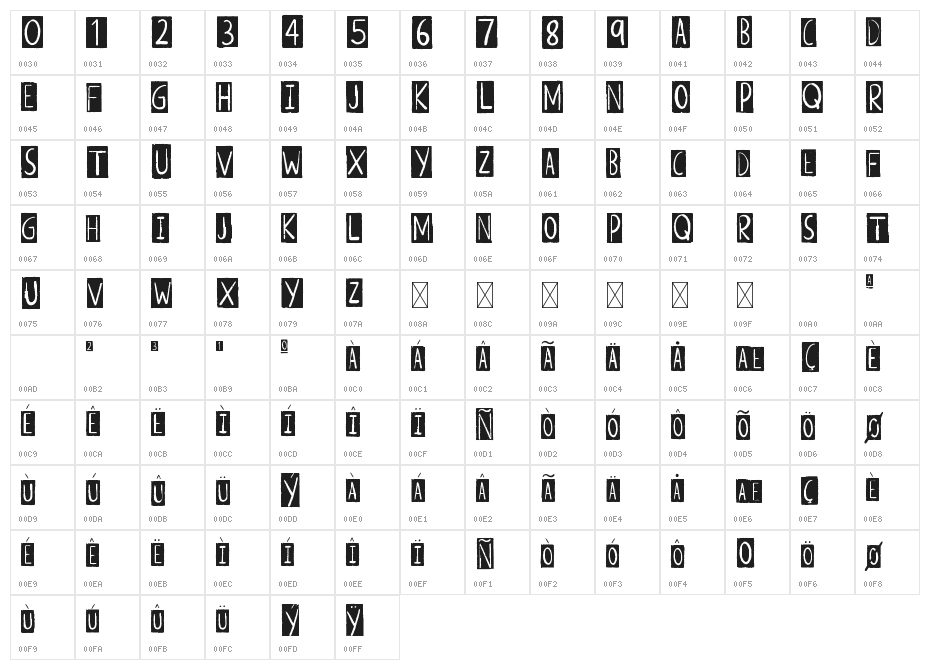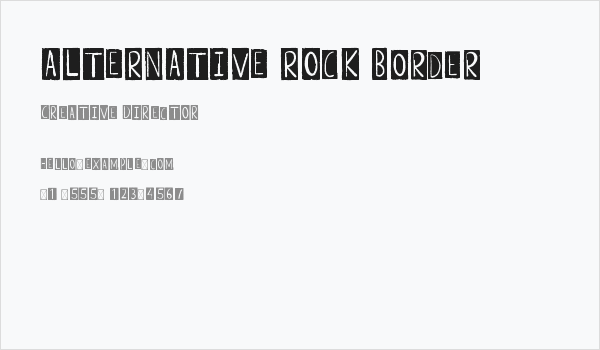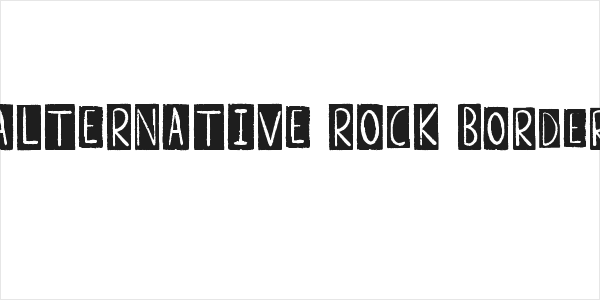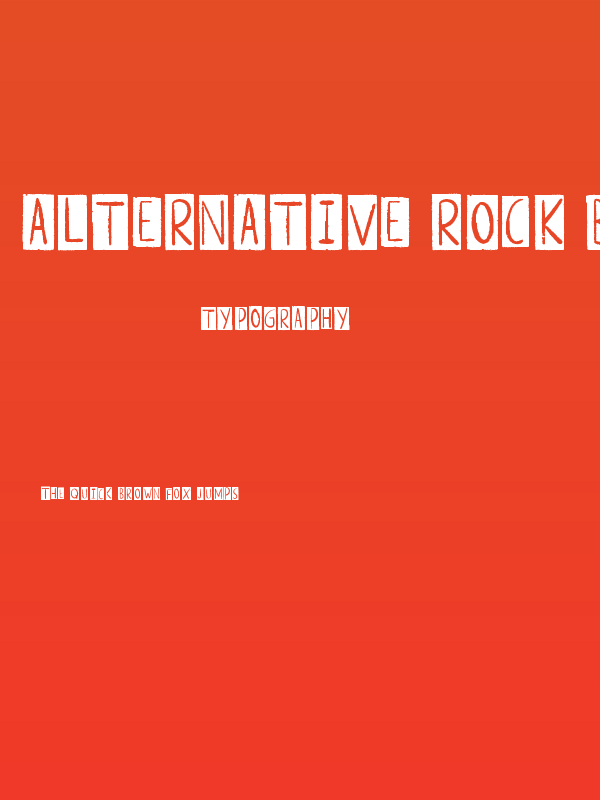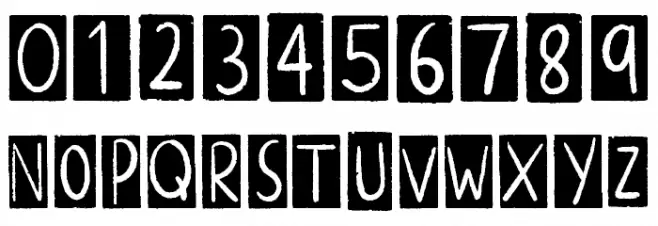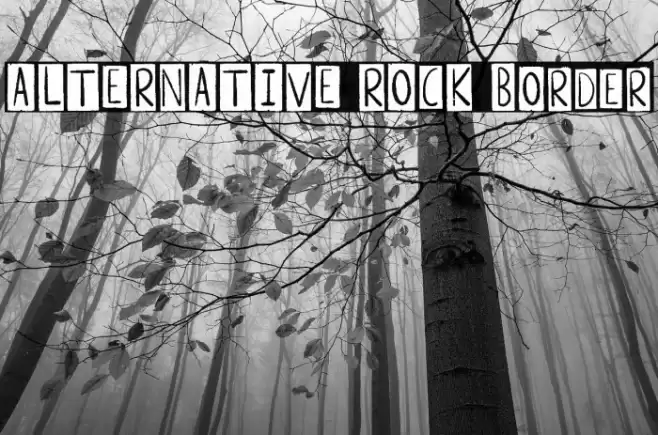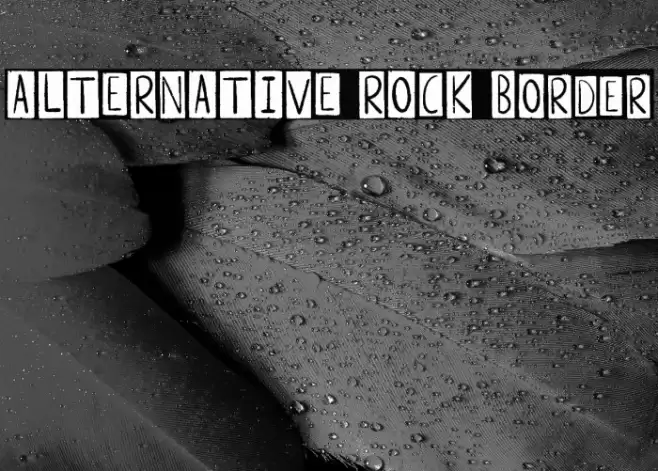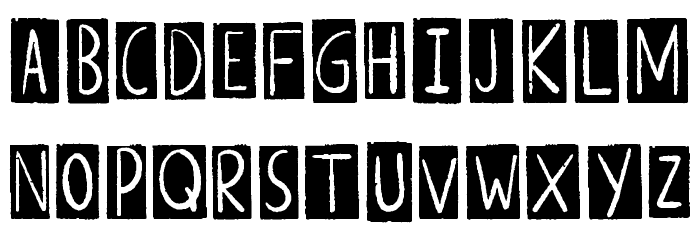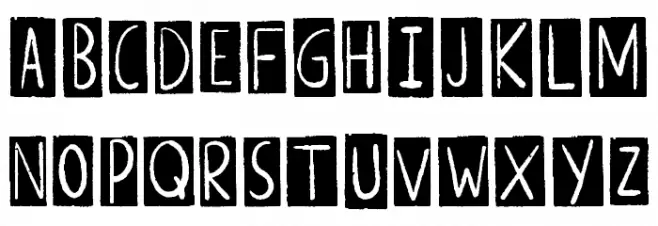
ALTERNATIVE ROCK Border Font
✎ Decorative
| 分类 | Decorative |
| 推荐项目 | Ideal for music album covers, posters, branding for edgy or alternative brands, and creative projects that require a bold statement. |